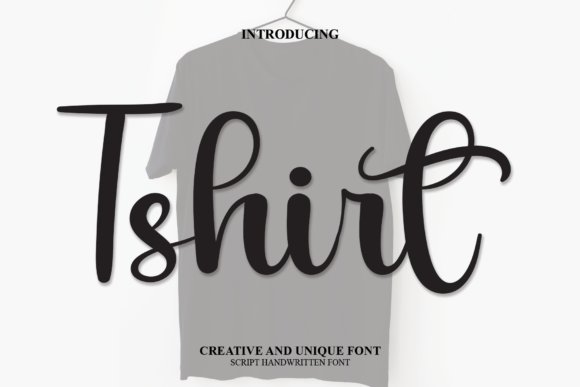
Tshirt
Tshirtのような高品質の素材をお探しの場合、このプレミアムパッケージはクリエイティブなプロジェクトに素晴らしい選択です。
精密に作られたTshirtは、クリーンなベクター、滑らかなタイポグラフィ、そして安心のための商用ライセンスを提供します。
POD(オンデマンド印刷)製品、結婚式の招待状、またはソーシャルメディアのグラフィックを作成している場合でも、Tshirtは理想的です。